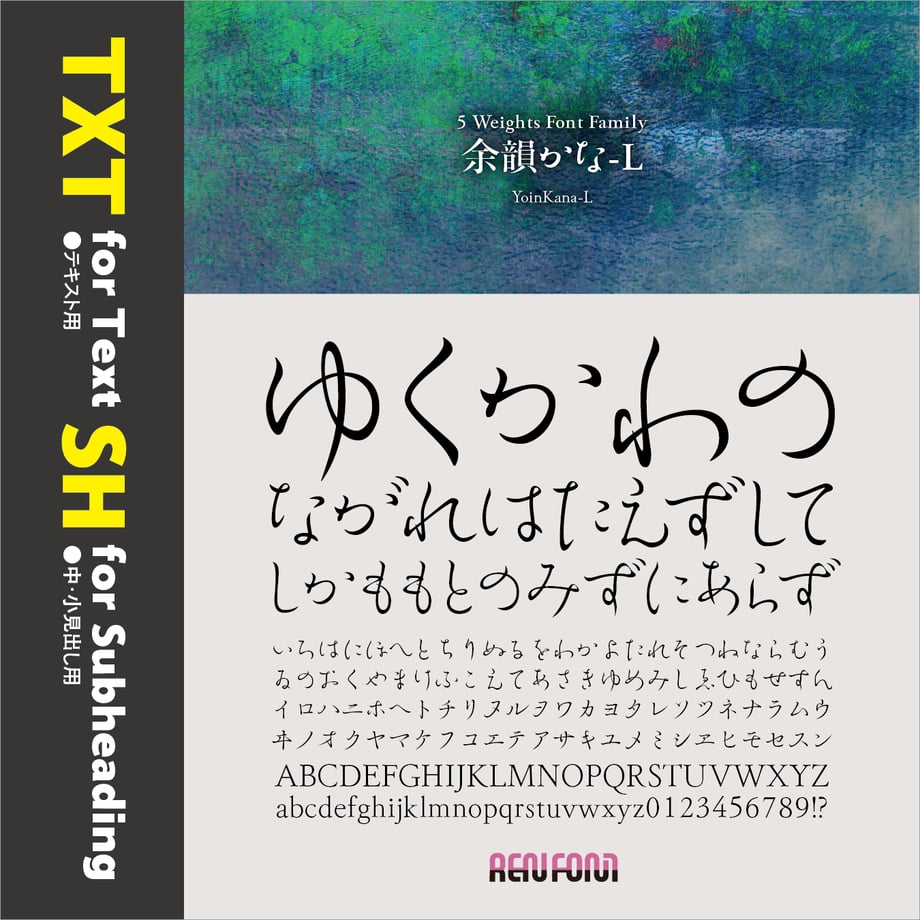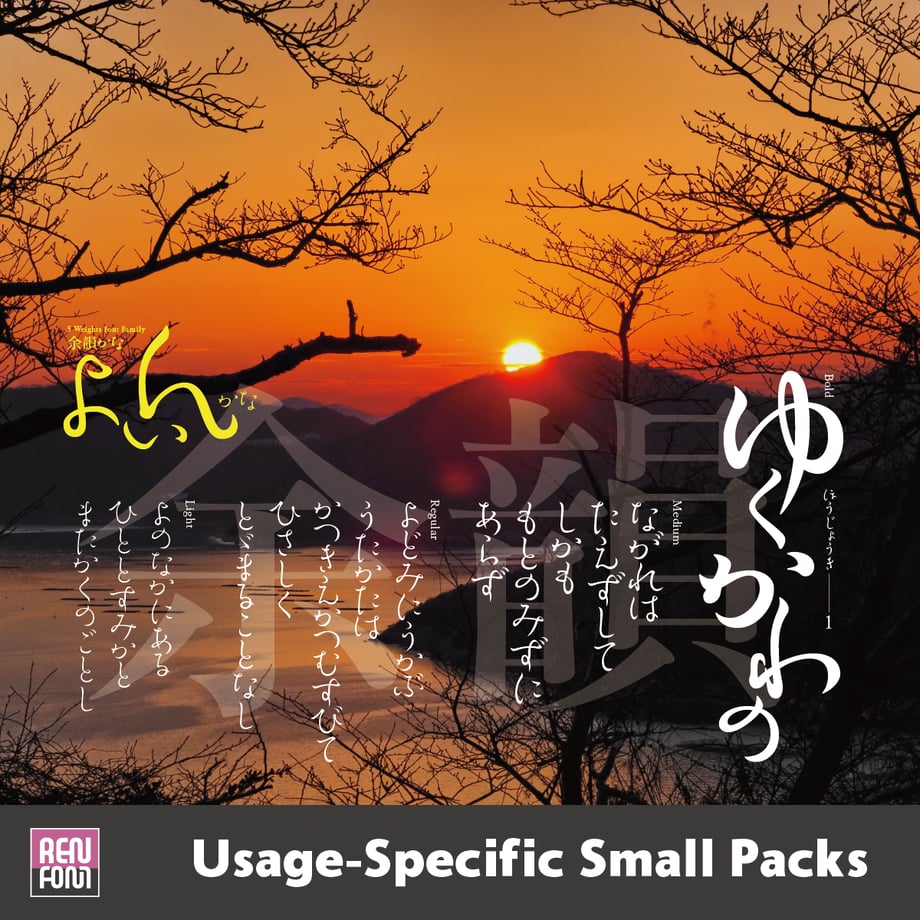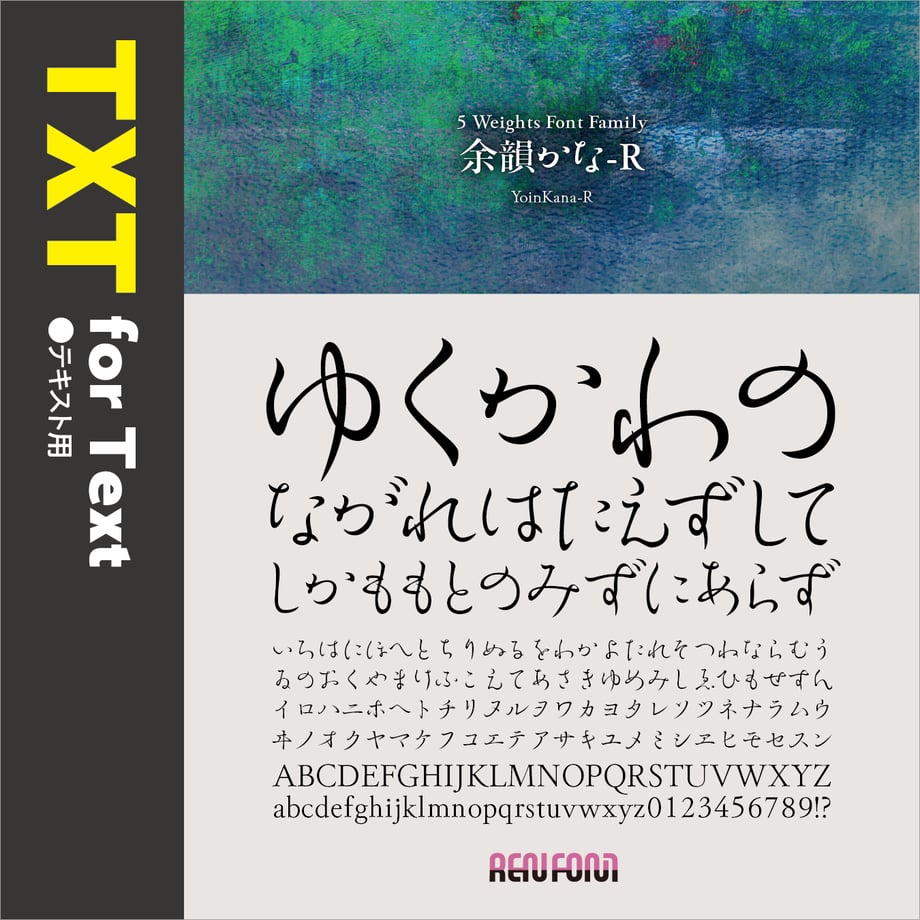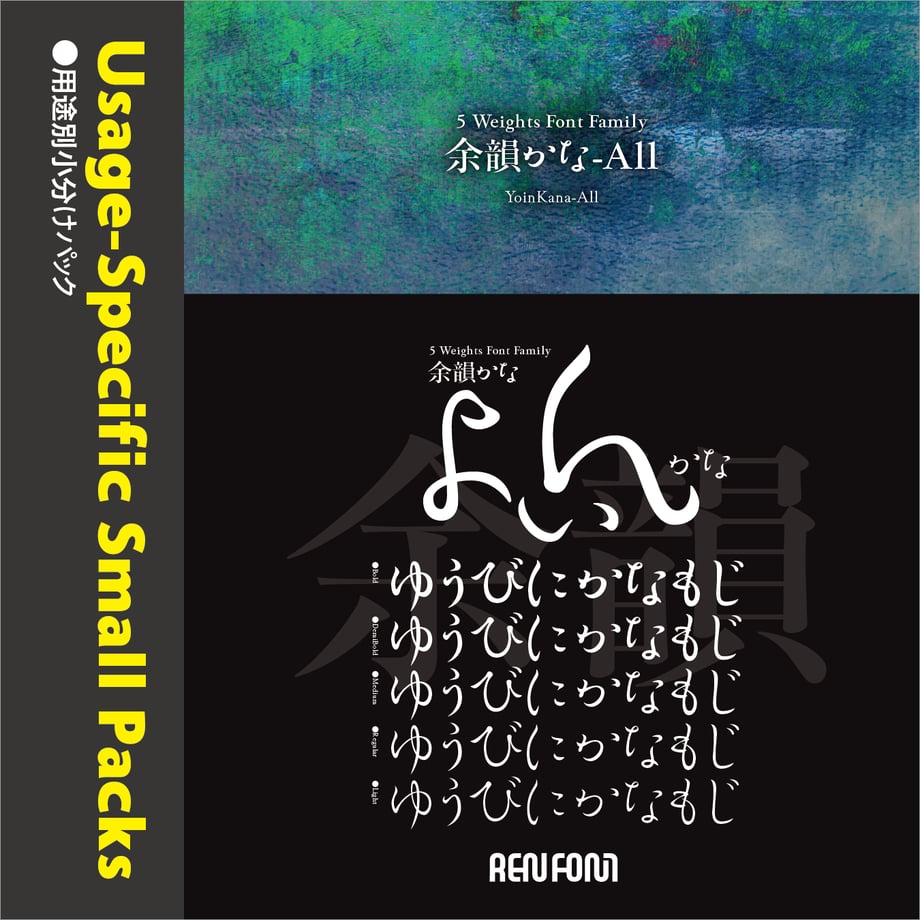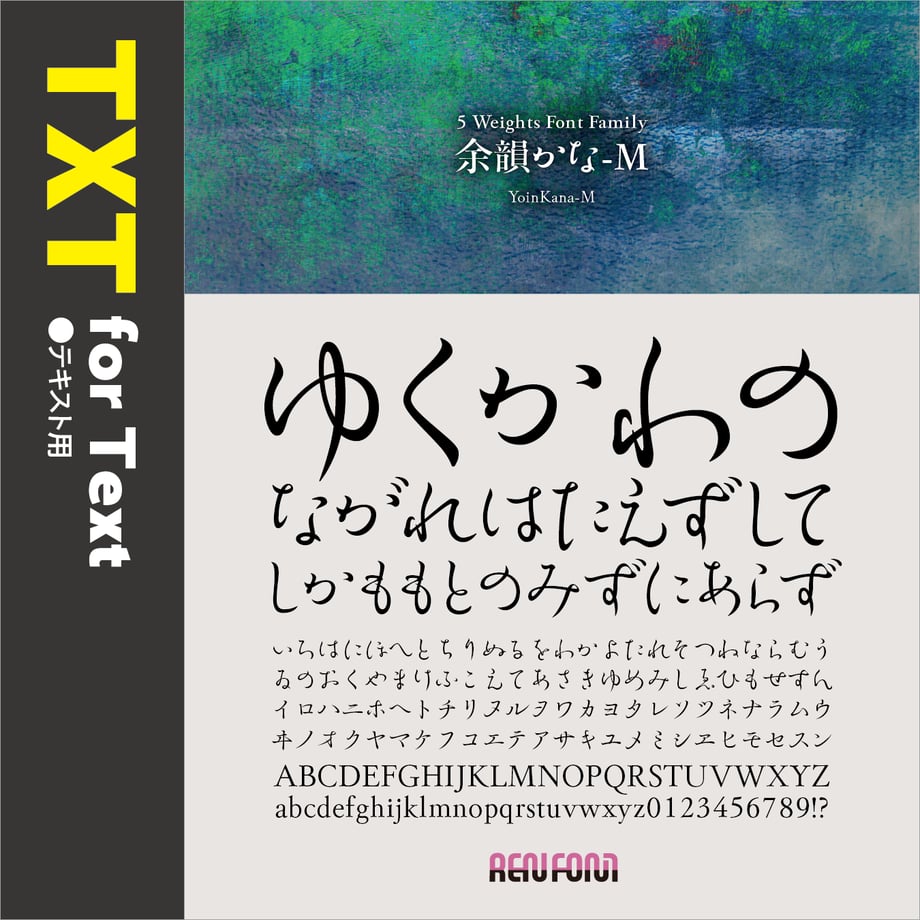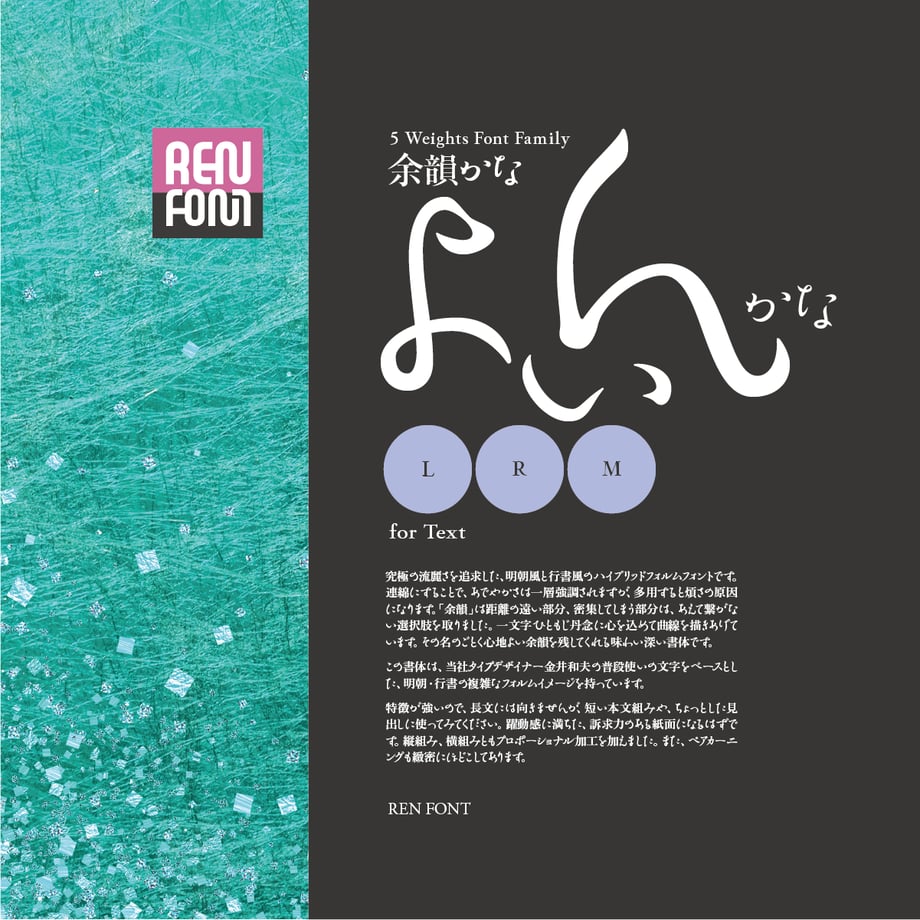
余韻かな-TXT(テキスト用)L/R/M
味わい深い余韻を残す
余韻かな 5ウェイトファミリー / OpenType
味わい深い余韻を残す印象的な書体。
究極の流麗さを追求した、明朝風と行書風のハイブリッドフォルムフォントです。連綿にすることで、あでやかさは一層強調されますが、多用すると煩さの原因になります。「余韻」は距離の遠い部分、密集してしまう部分は、あえて繋がない選択肢を取りました。一文字ひともじ丹念に心を込めて曲線を描きあげています。その名のごとく心地よい余韻を残してくれる味わい深い書体です。
この書体は、当社タイプデザイナー金井和夫の普段使いの文字をベースとした、明朝・行書の複雑なフォルムイメージを持っています。「L(ライト)」、「R(レギュラー)」、「M(ミディアム)」、「DB(デミボールド)」、「B(ボールド)」の、合計5ウェイトで構成されています。
また、オールドなイメージを残しつつも、その概念にとらわれず大仮名に設計してあるので、近代的な組版にも対応するマルチな性格を備えています。
舞踊・舞踏の心や動きを表現する
余韻かなファミリーの各書体は、まるで日本舞踊のような優雅さ、ワルツのような軽快さを表現しています。ほとんどの文字が正統派の明朝体からはかけ離れたフォルムをしていながら、訴求力や優美さを損なわないよう、細心の注意を払いました。
特徴が強いので、長文には向きませんが、短い本文組みや、ちょっとした見出しに使ってみてください。躍動感に満ちた、訴求力のある紙面になるはずです。縦組み、横組みともプロポーショナル加工を加えました。また、ペアカーニングも緻密にほどこしてあります。
日本語文章の約70%はひらがな、カタカナが占めているといわれます。それだけに紙面の雰囲気を左右し、決定づける重要なアイテムです。
余韻かなのウェイトは5つ。本来、長文に向かない書体ですが、伝統的なオールド書体の雰囲気も持ち合わせており、一番使用頻度の高いLウェイトも制作しました。微妙な太さの違いがあるので、用途は意外に広いかも知れません。
そのフォルムは、しなやかでなめらか。払いを強調して舞踊のような躍動感を演出します。先端は全て丸く処理、終筆も文字により独特の形にしてあります。カタカナは、その最大の特徴である「直線的フォルム」を残し、ひらがなの曲線を加味しバランスを取るという難しさにあえて挑戦した野心作となっています。
欧文・数字は、奔放な両かなとは異なり、クセの少ない伝統的なイメージにデザインしました。わずかに「K」「Q」「R」のテールに「かな」の雰囲気を持たせてあります。
格調高いGaramond調の形状ですが、若干現代風な設計になっています。欧文書体としての単独使用にも十分に耐えうる、和文付嘱書体としては稀な、非常に高い完成度を持っています。